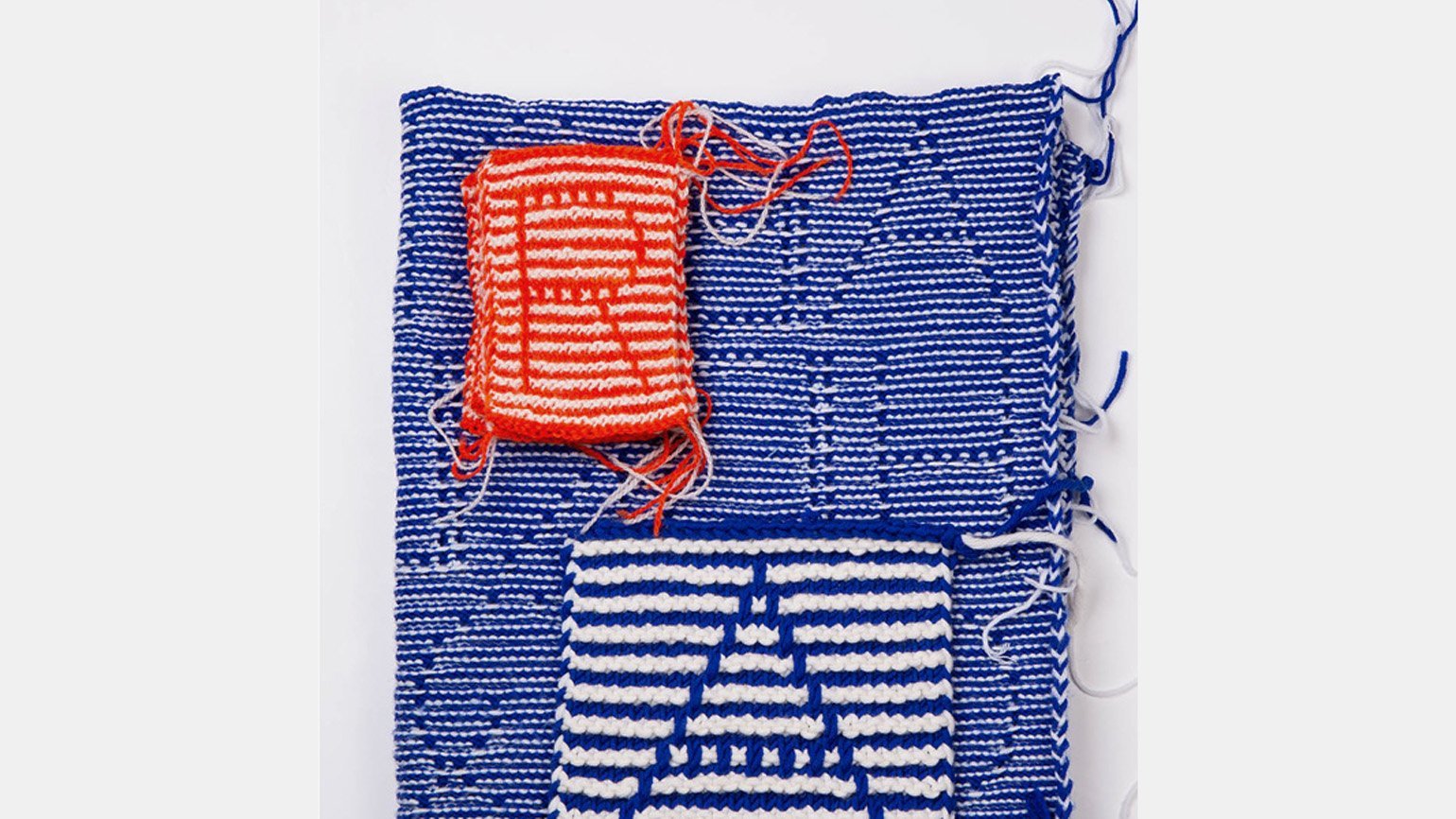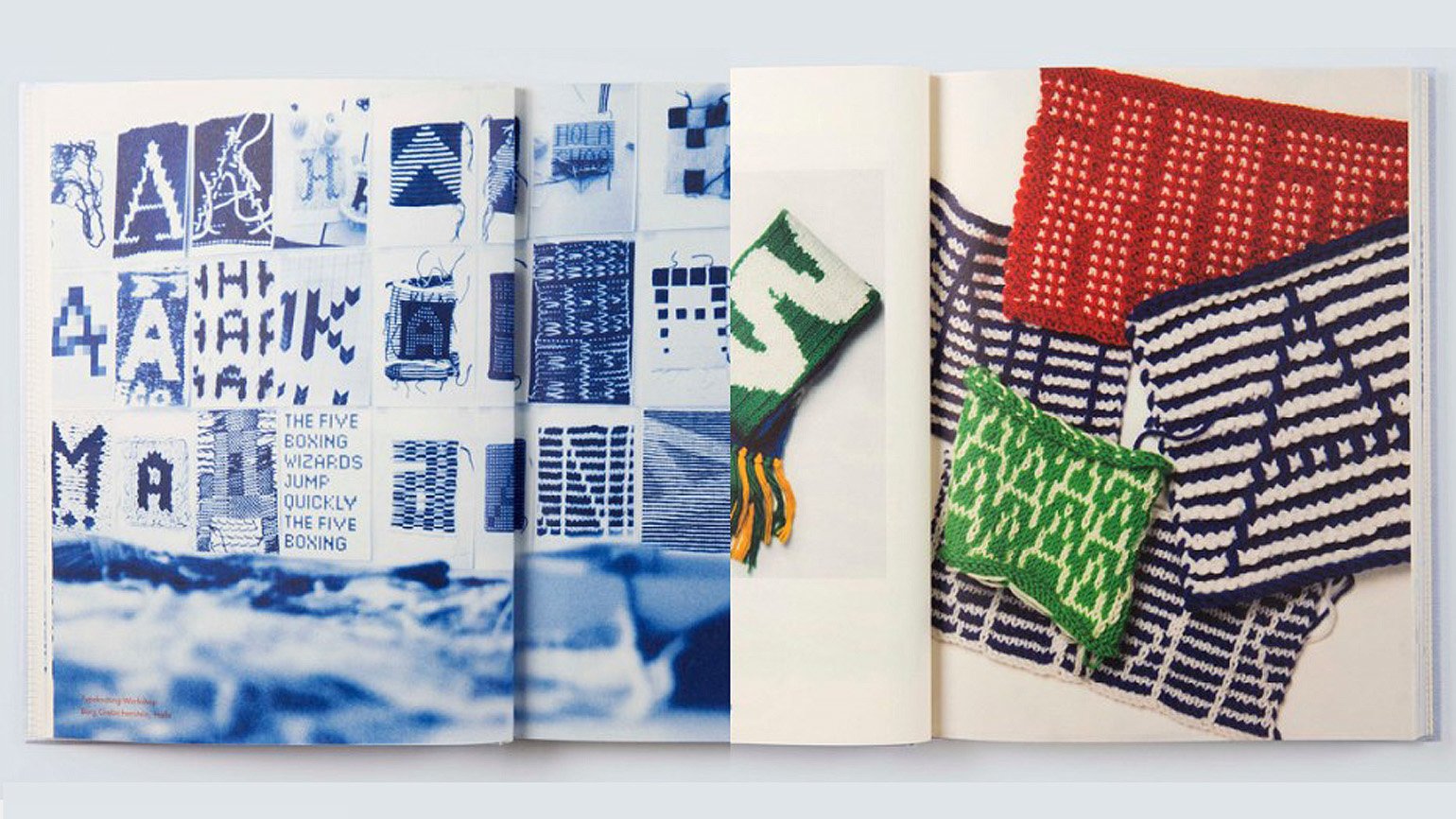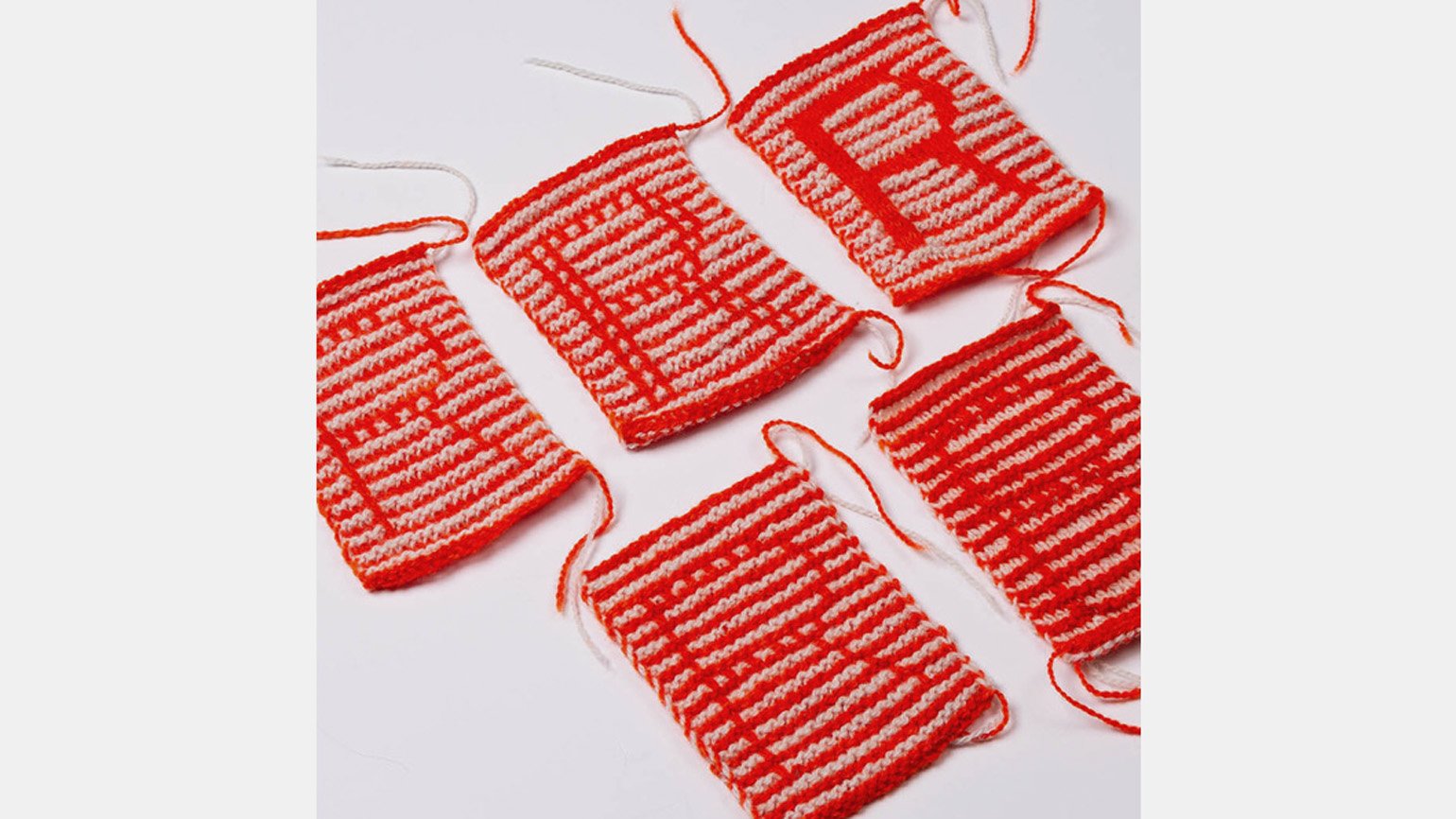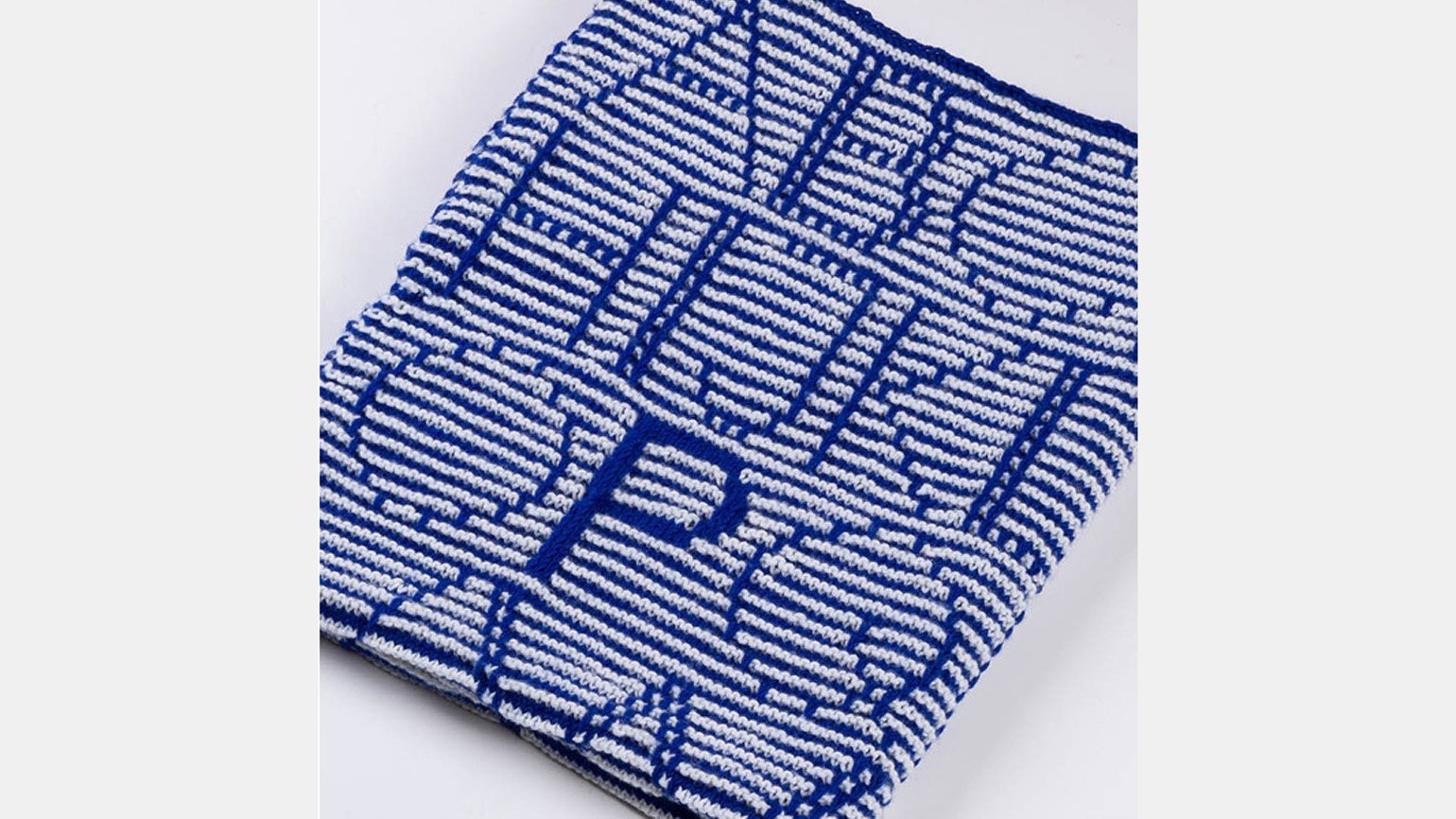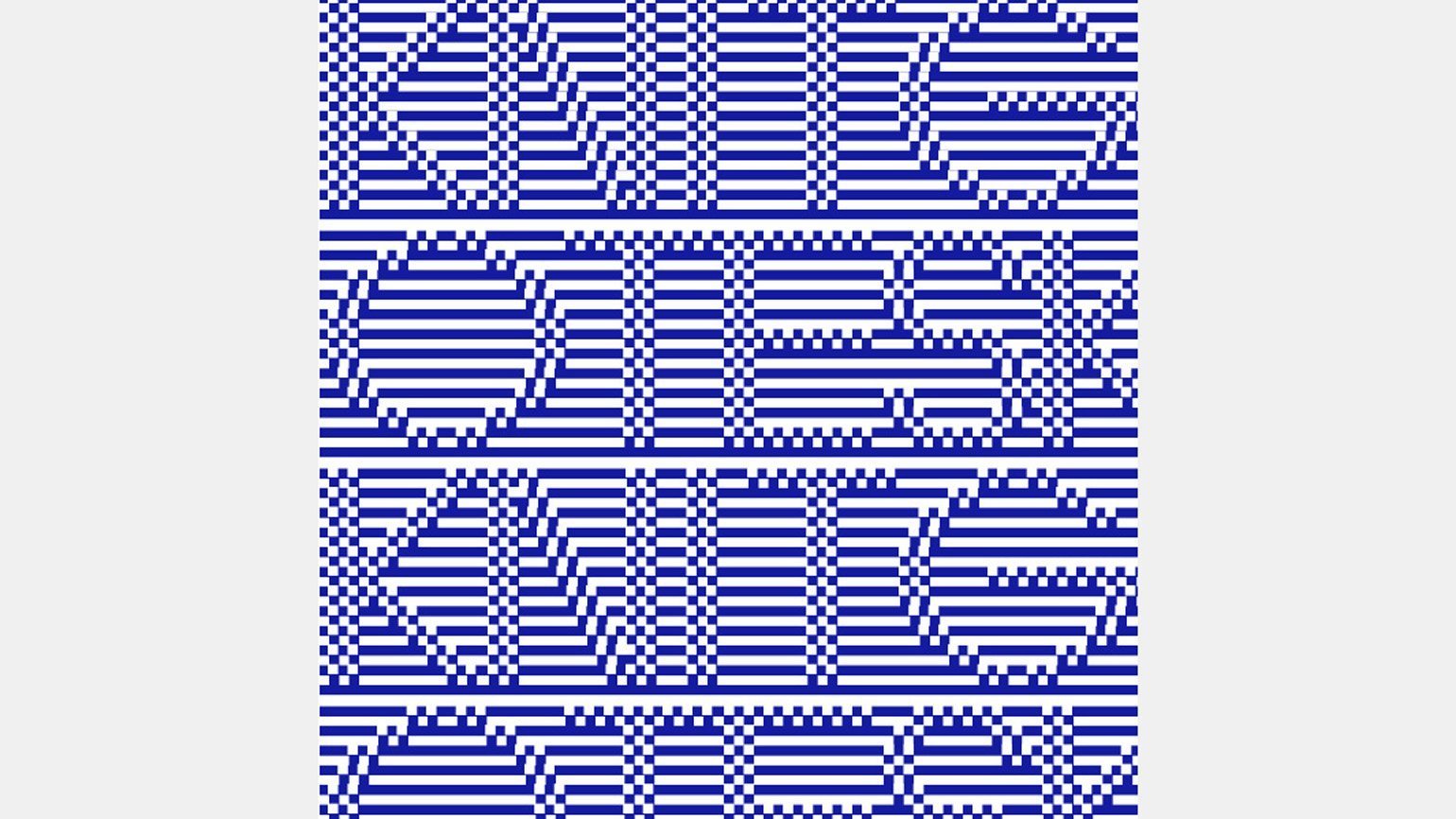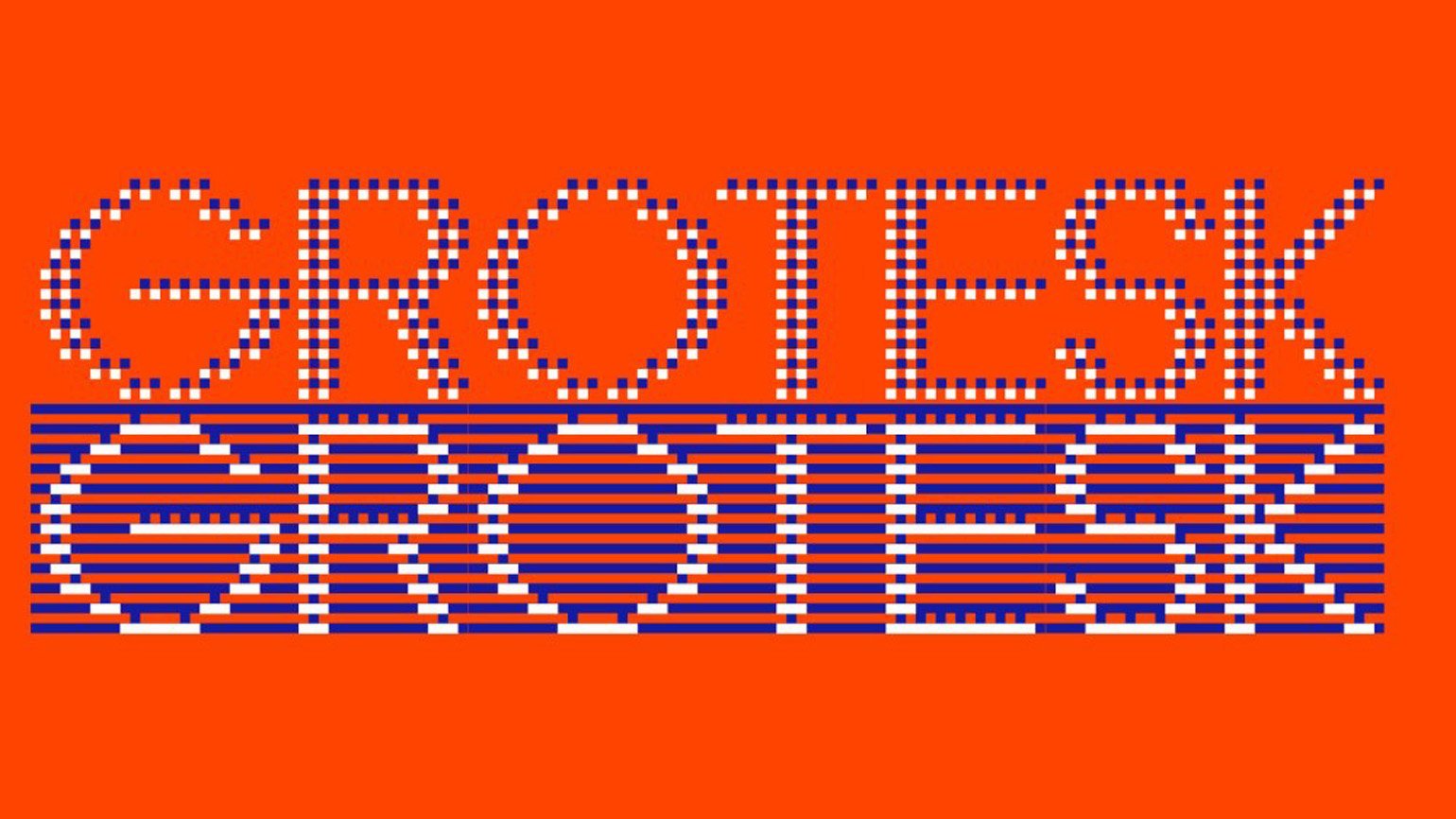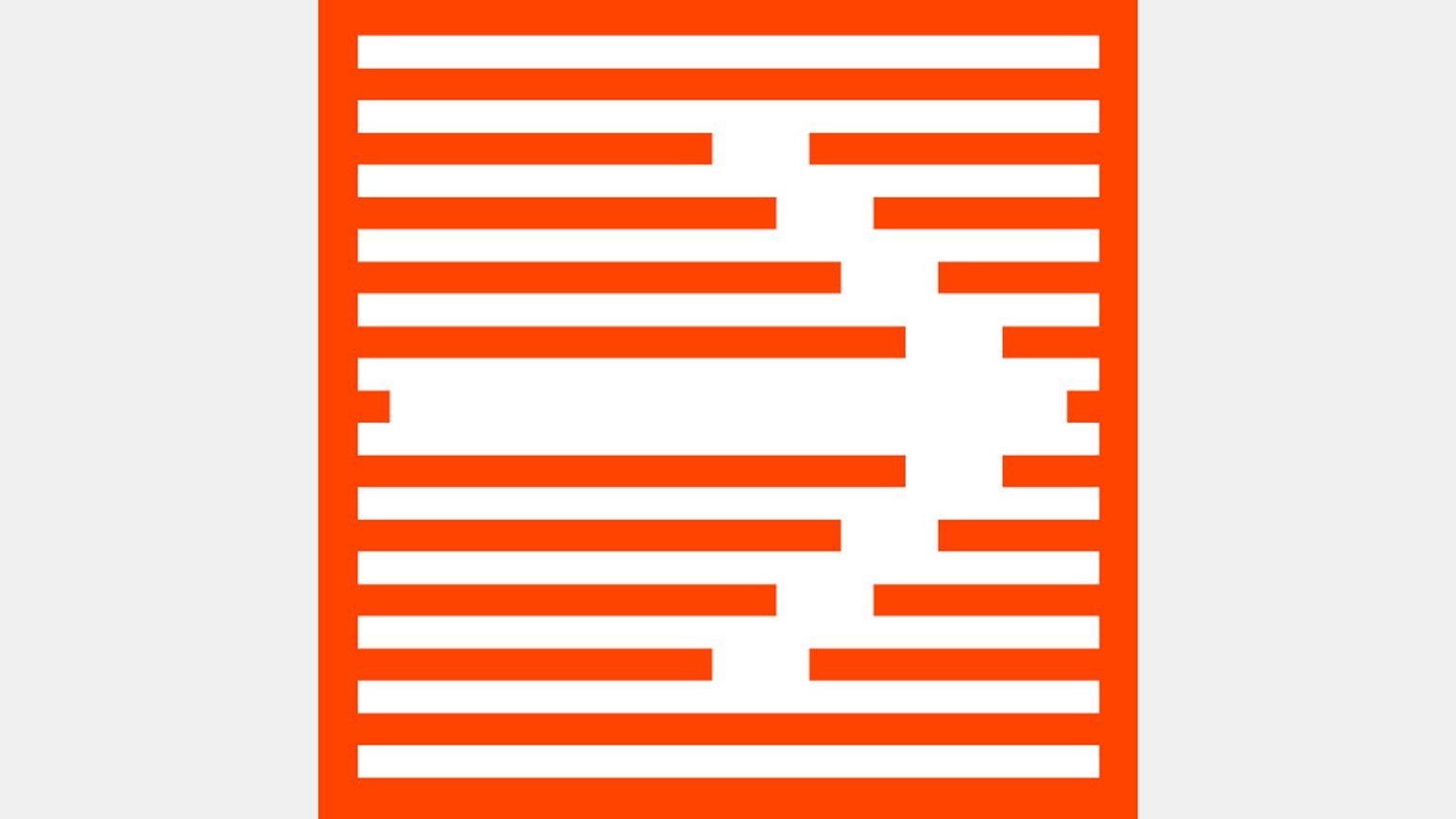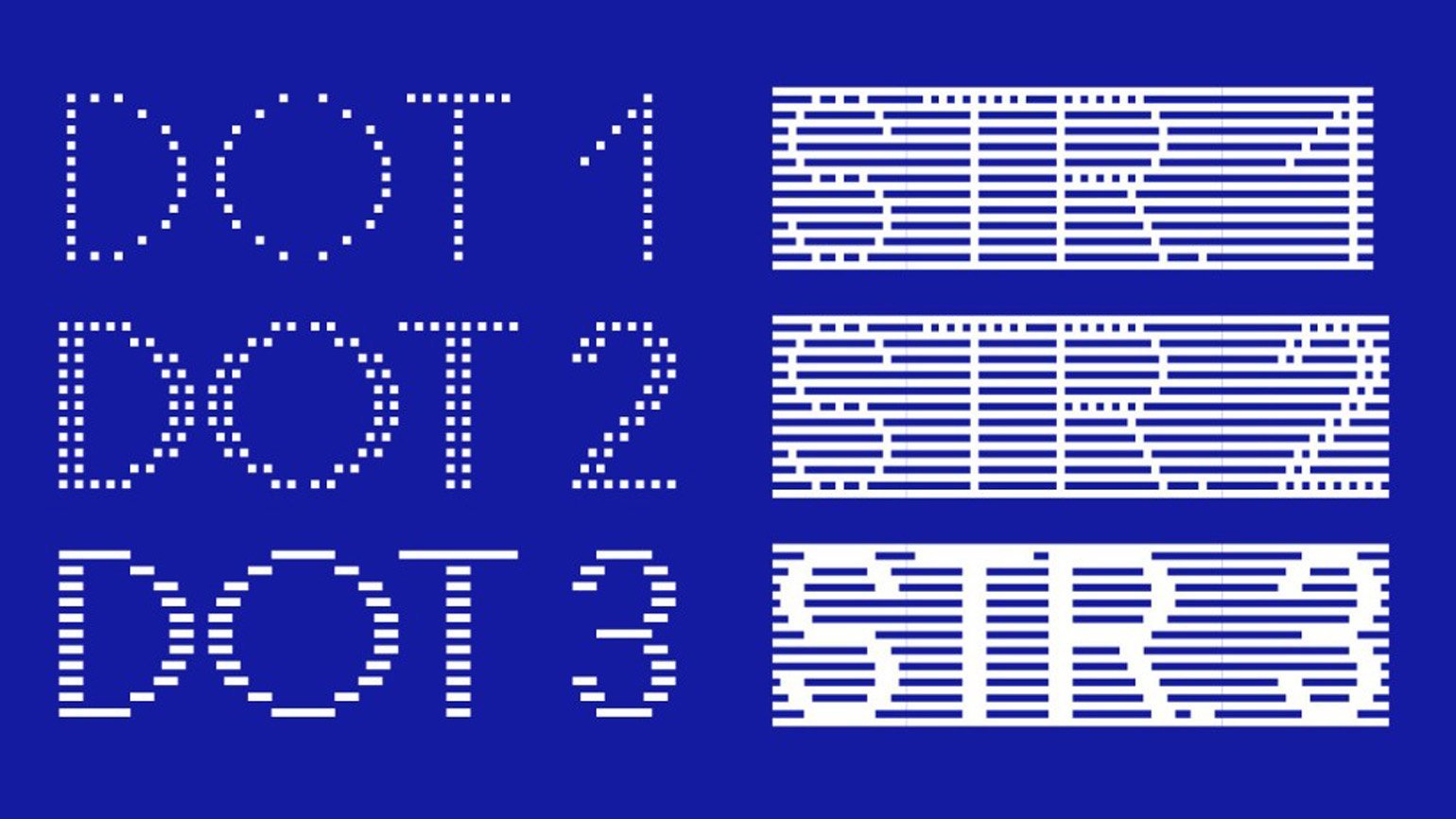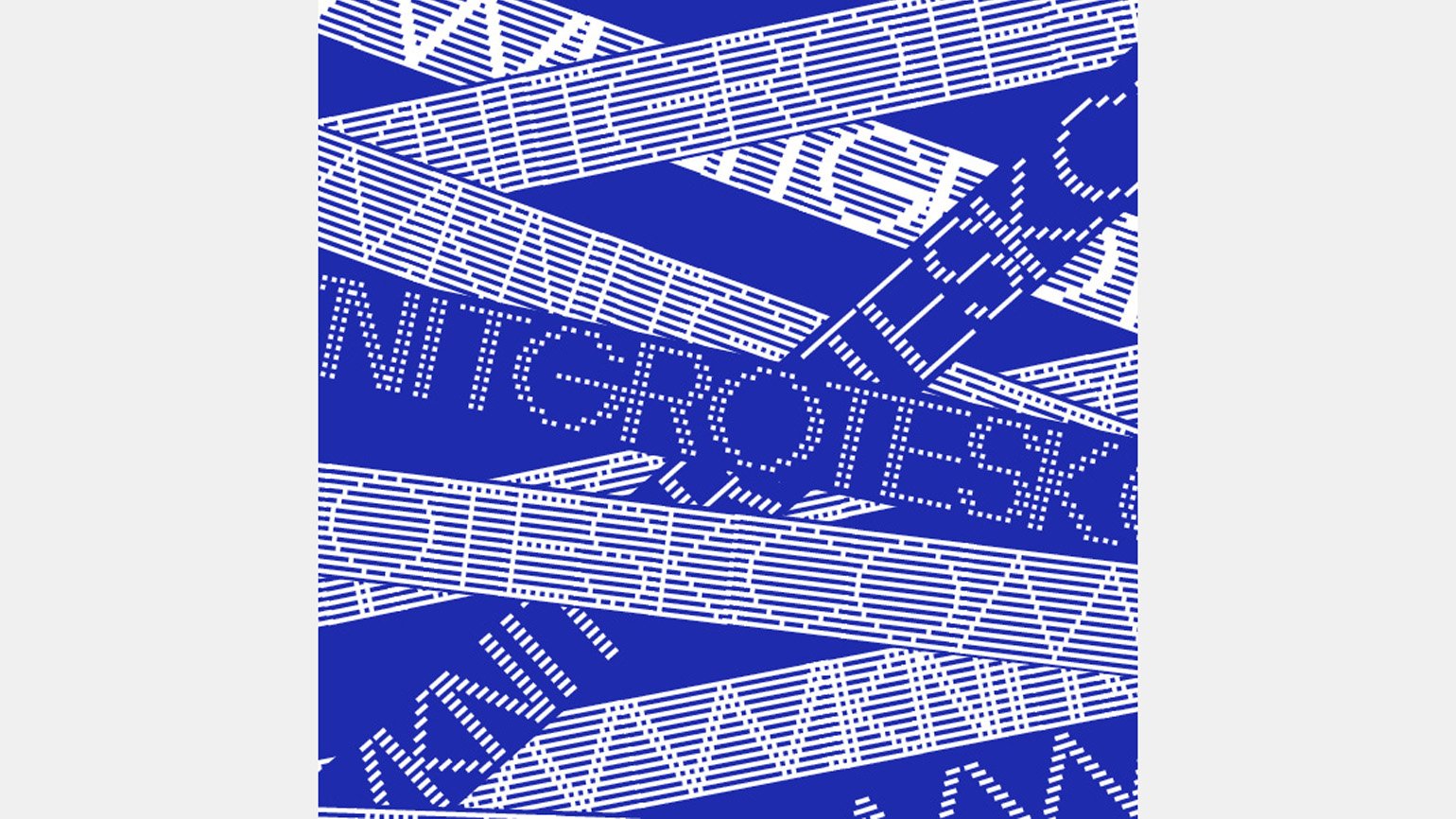
Дизайнер Рюдигер Шлёмер разработал шрифт, который можно связать
С помощью Knit Grotesk можно сделать свитер или шарф с любой надписью самостоятельно.
Рюдигер Шлёмер, дизайнер из Цюриха, работает на стыке текстильного дизайна и типографики. Он разработал Knit Grotesk — шрифт, специально предназначенный для вязания. Пиксельная гарнитура хорошо выглядит как на экране, так и на ткани, а ещё она отлично подходит для ярких цветовых сочетаний и интересных текстур. Шрифт применим в любых других ремёслах, где возможна пиксельность. Например, в мозаике или архитектуре.
Свои исследования типографского вязания дизайнер обобщил в книге «Пиксель, заплатка и узор» (Pixel, Patch und Pattern. Typeknitting). Он регулярно проводит семинары и мастер-классы.
Пример паттерна с Knit Grotesk
Шрифт Knit Grotesk был вдохновлён адаптацией классического геометрического гротеска Futura для низкого разрешения (FuturX от Laucke Siebein). Шлёмер перевёл эту вариацию шрифта в схему ручного вязания. В процессе возник целый набор типографских деталей, и в итоге получился самостоятельный шрифт. Наиболее характерный его элемент сетка из вертикальных линий создаётся за счёт чередующихся двухцветных двойных рядов, которые получаются при вязании изнаночными петлями.
Книга «Пиксель, заплатка и узор»
Шрифт содержит акценты, альтернативные буквы и лигатуры. Благодаря сочетанию трёх насыщенностей гарнитуры с сеткой из вертикальных линий и точек получилось шесть вариаций.
«Пиксель, заплатка и узор»
Пример паттерна с Knit Grotesk
Цифровое изображение Knit Grotesk